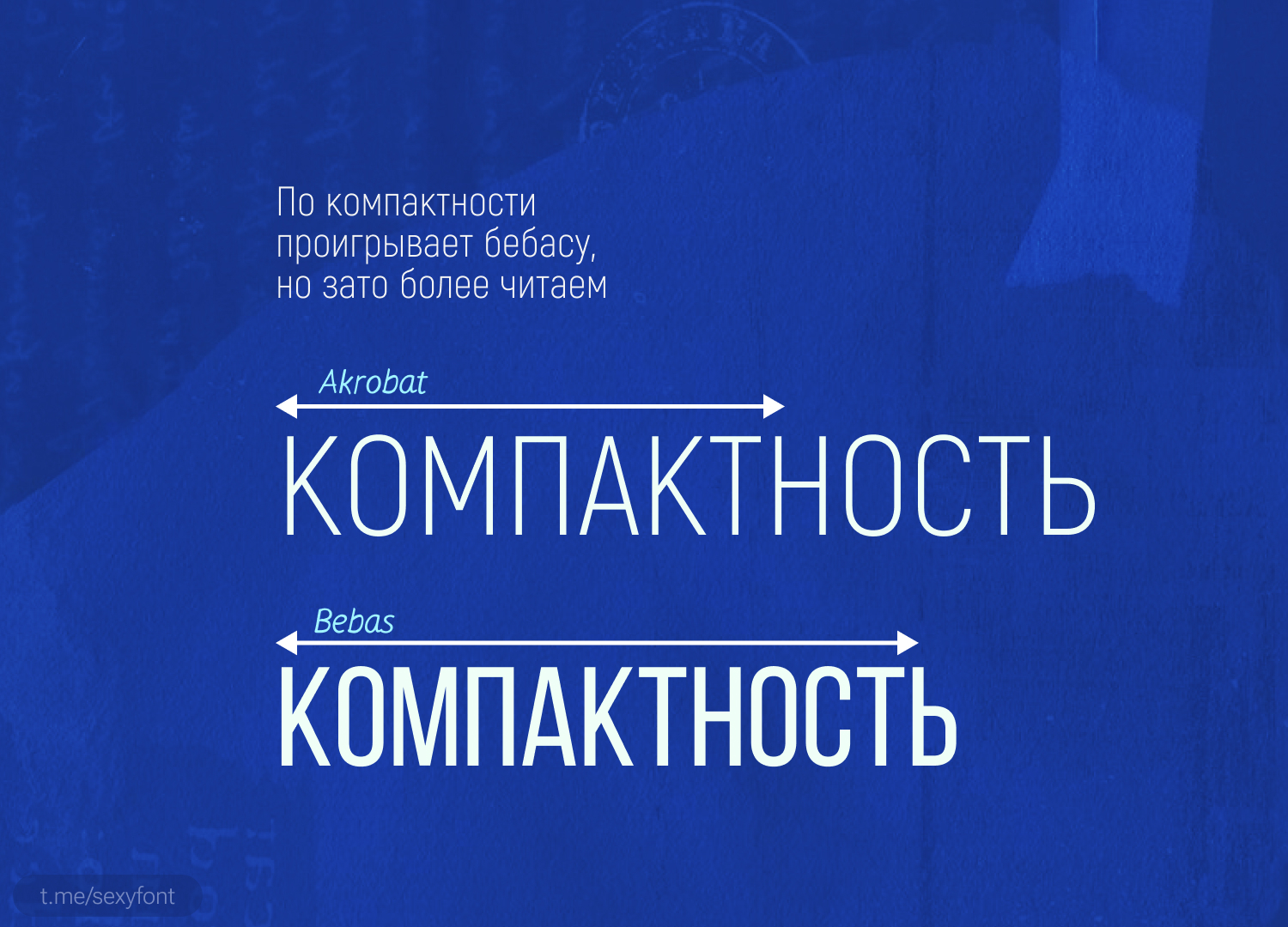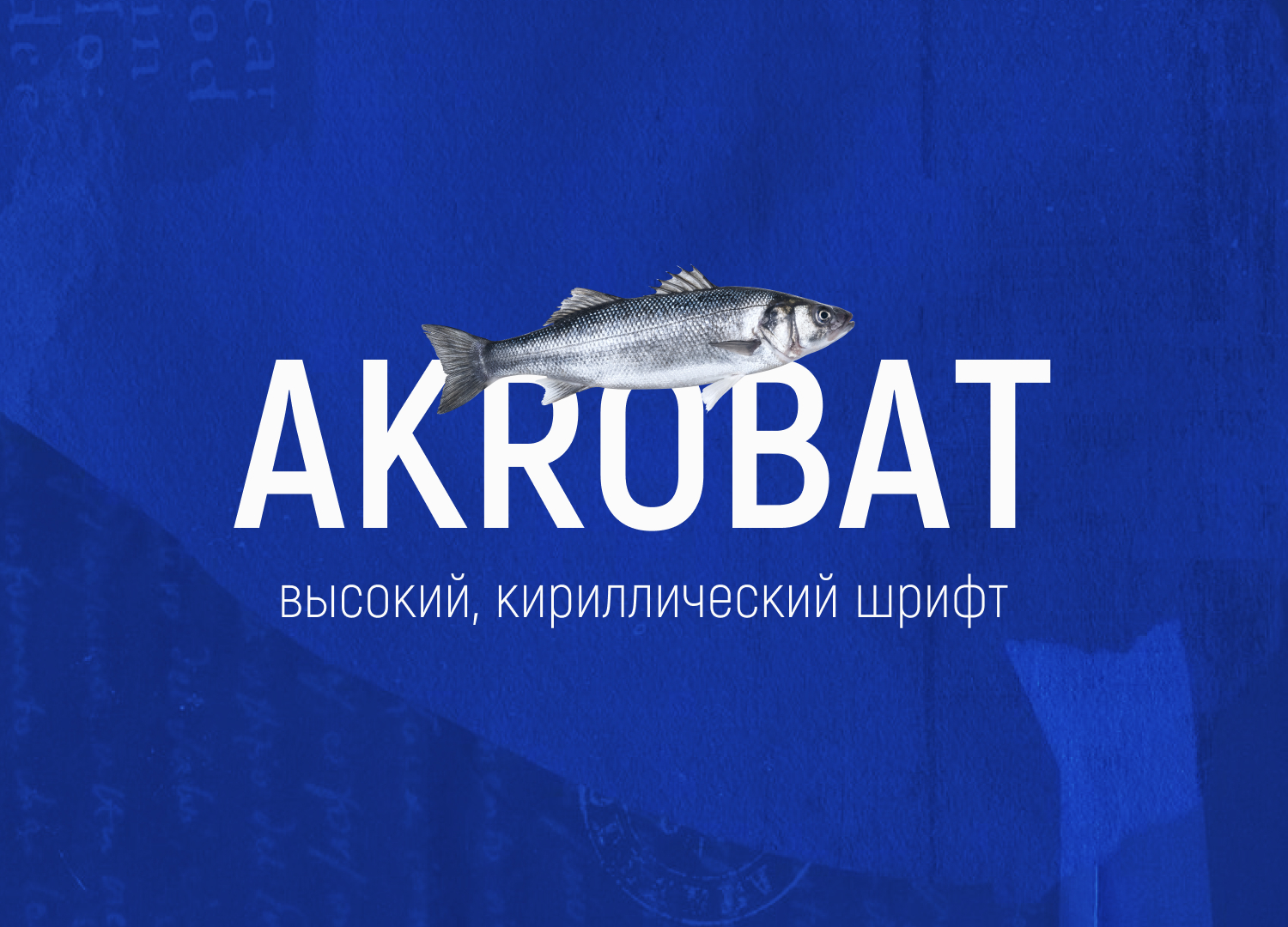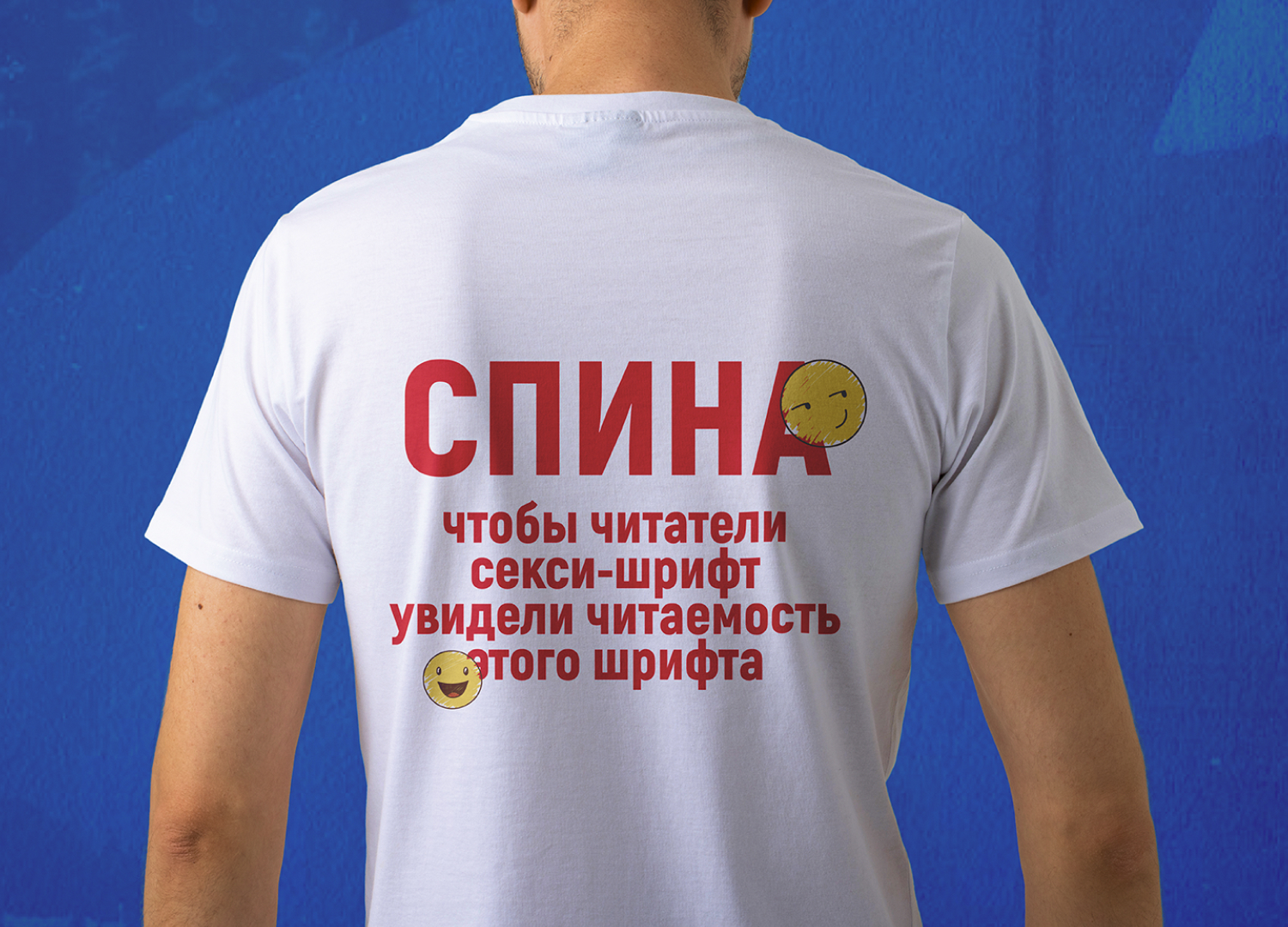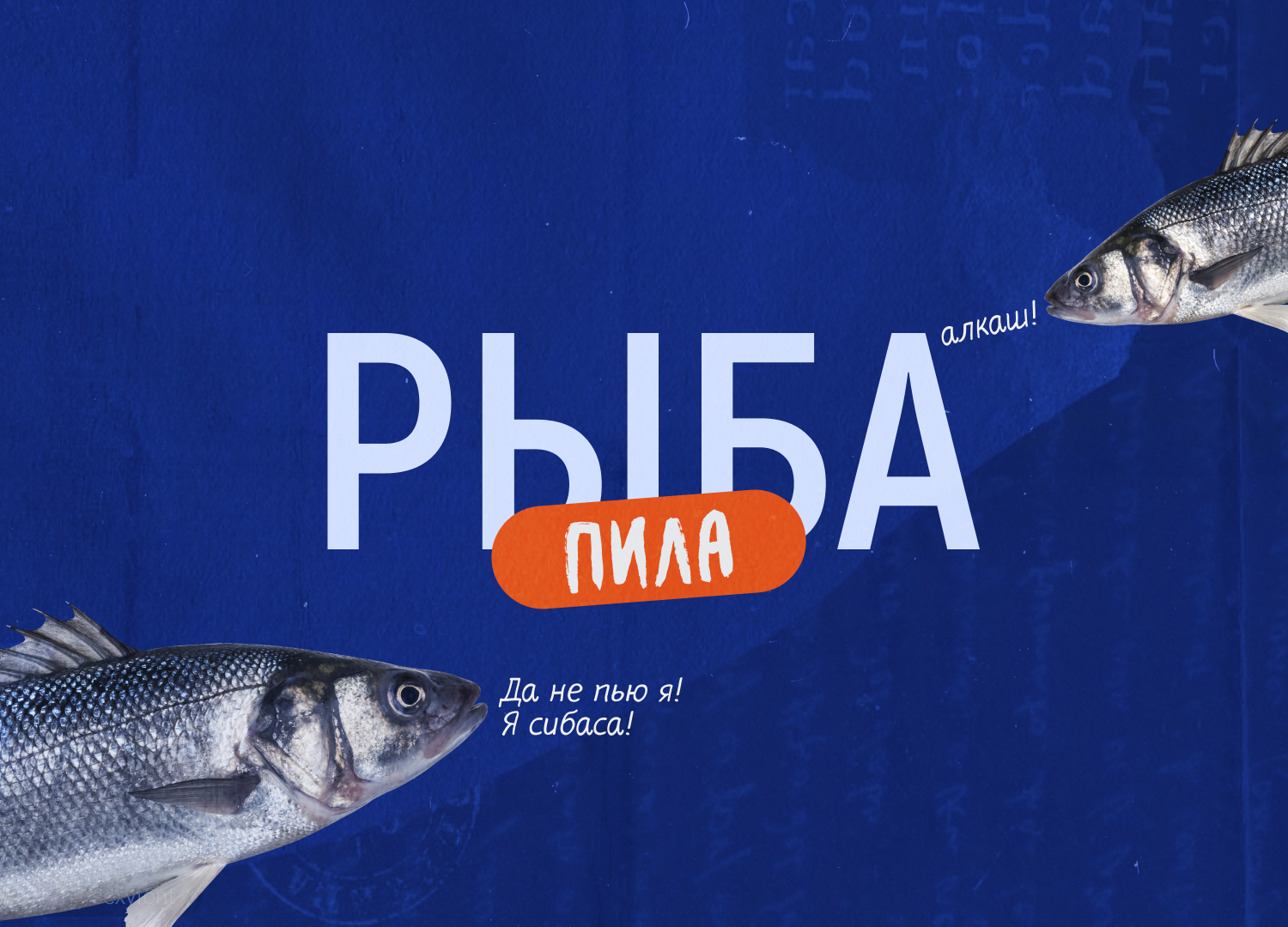
Старый добрый akrobat. Шрифт
Высокий и в меру вместительный шрифт. За это его и полюбили). Не баян, а классика. Я должен был сделать для него презентацию.